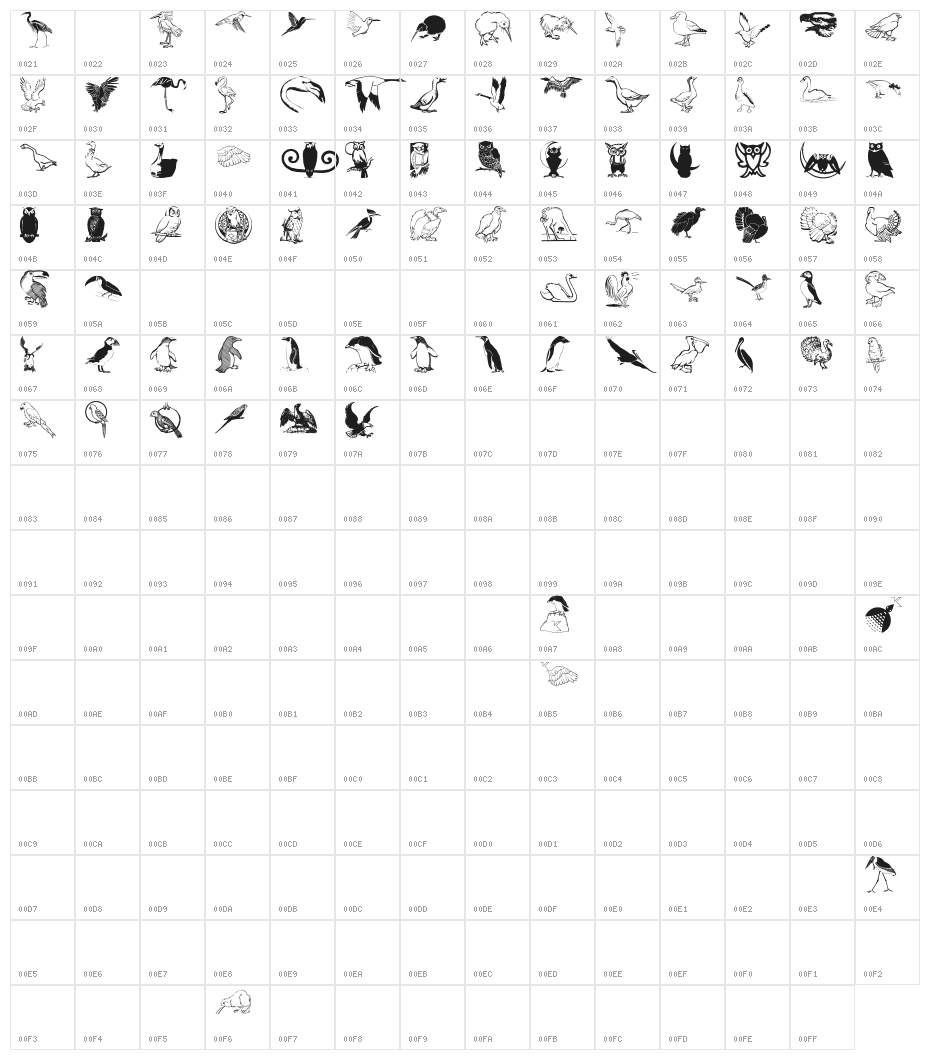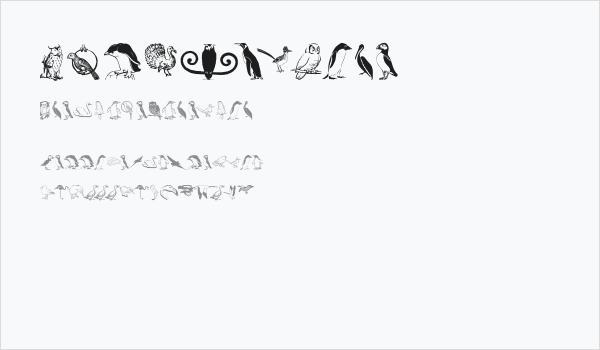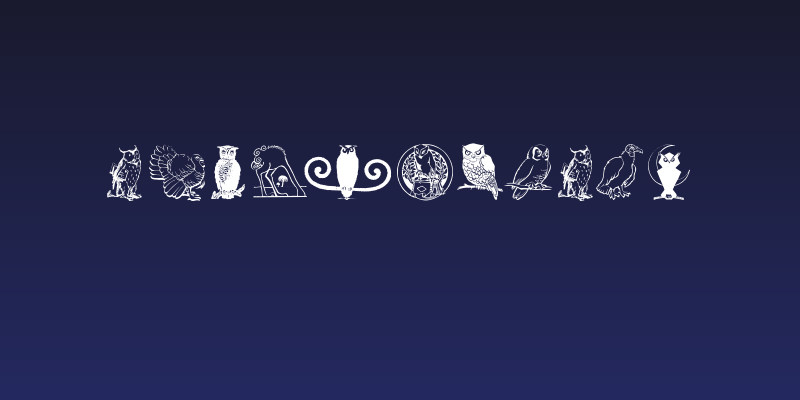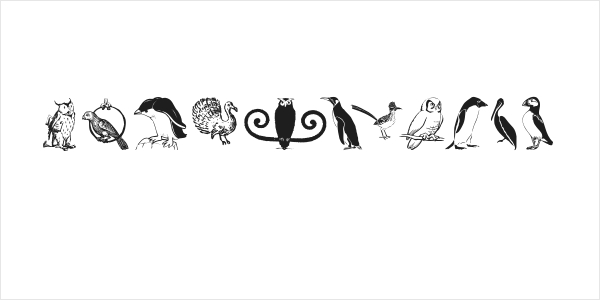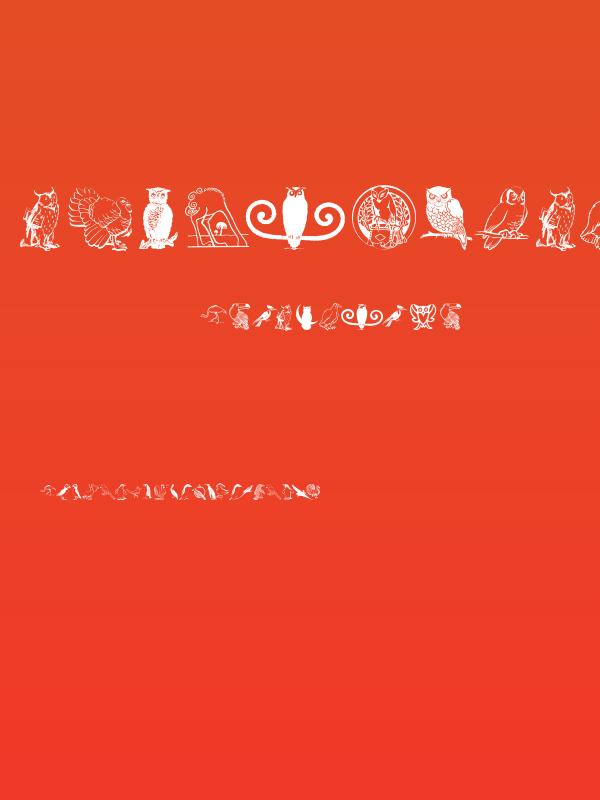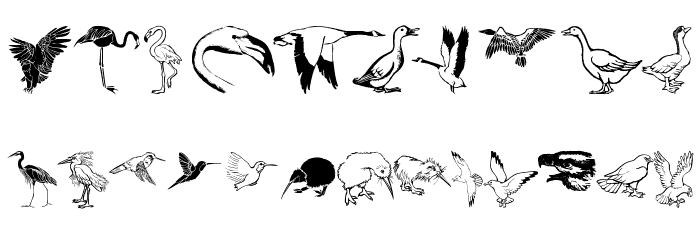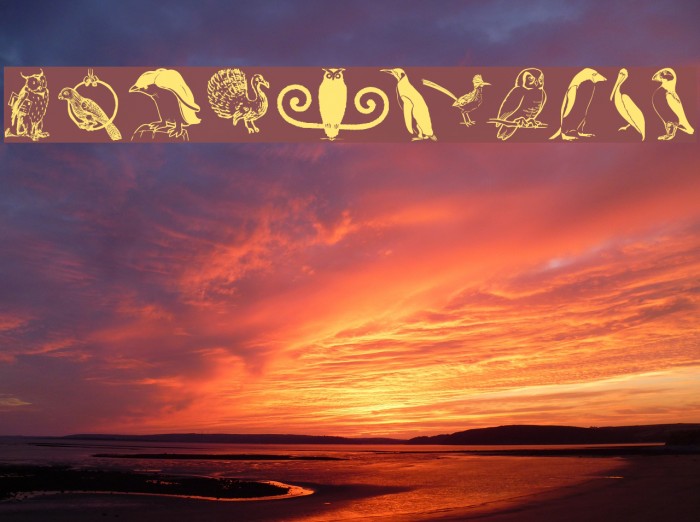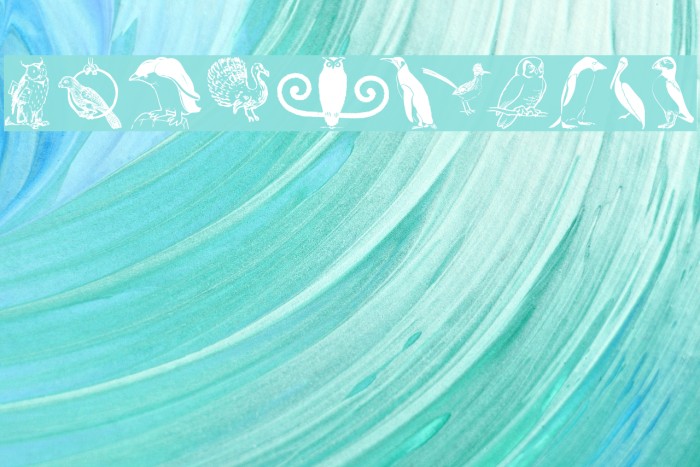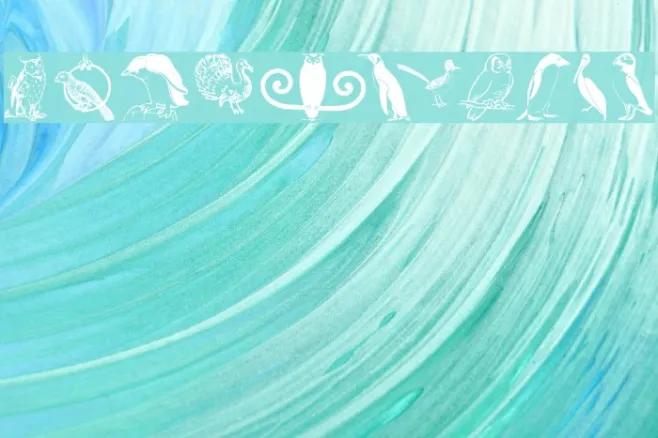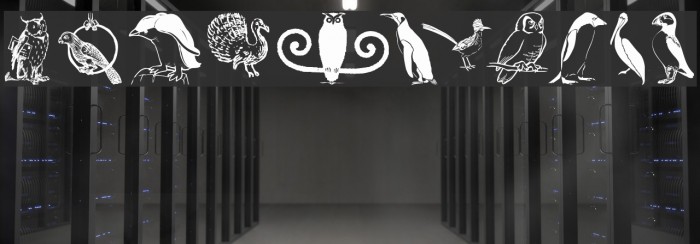
OwlsAndMore Font
| Stile generale | Decorative, Whimsical, Nature-inspired |
| Caso d'uso | Logos, Headlines, Themed graphics, Educational content |
| Progetti proposti | Children's books, educational materials, wildlife posters, themed invitations, creative branding. |